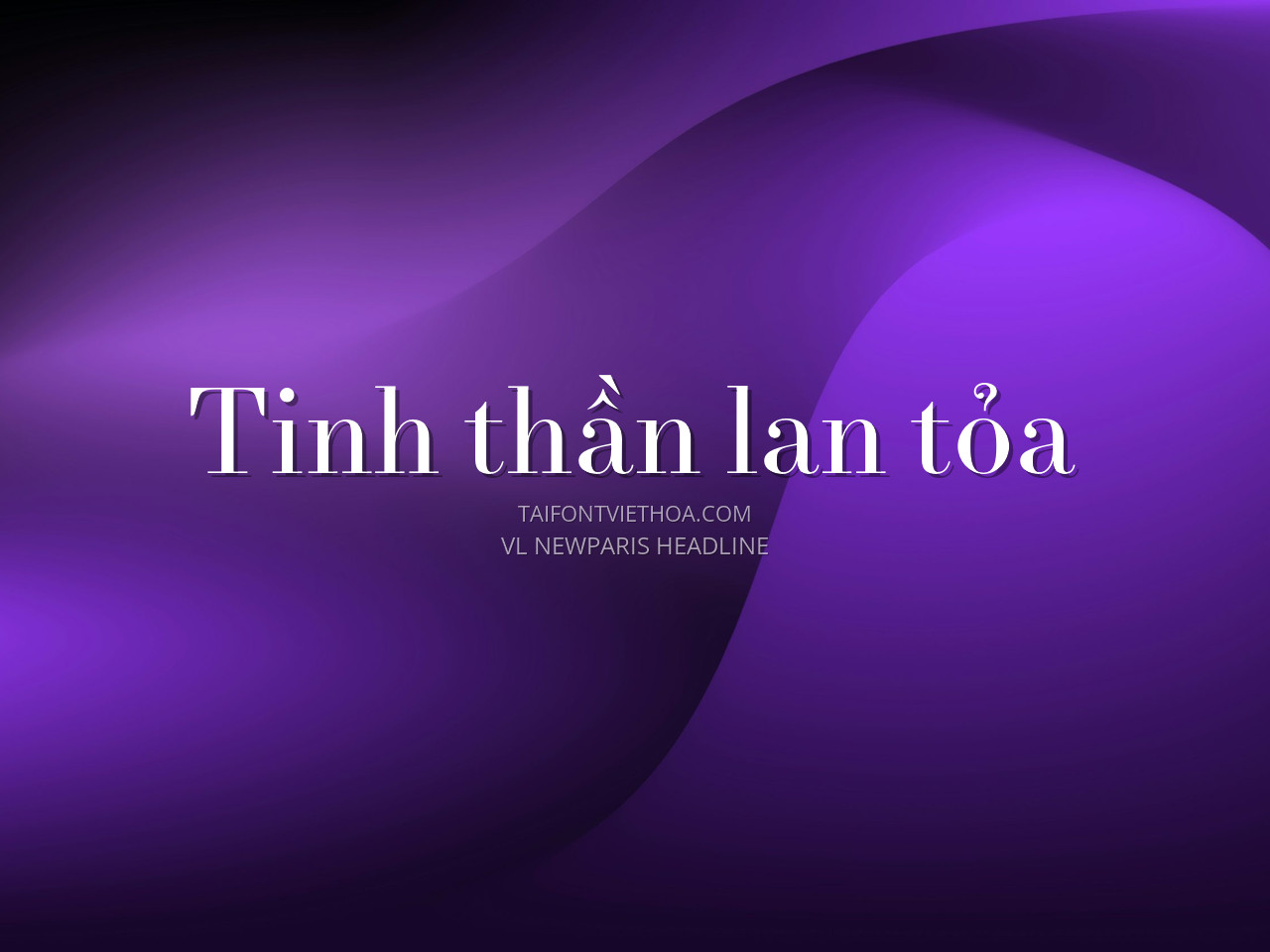
Font việt hóa VL Newparis Headline
Giới thiệu về font VL Newparis Headline
VL Newparis Headline là một kiểu chữ serif hiện đại cao cấp được thiết kế đặc biệt dành cho các tiêu đề lớn, tạo ấn tượng mạnh mẽ ngay từ ánh nhìn đầu tiên. Font mang đậm phong cách biên tập chuyên nghiệp, thường thấy trong các tạp chí thời trang, catalogue hoặc bộ nhận diện thương hiệu cao cấp. Phiên bản Việt hóa được thực hiện bởi Font Việt Linh, hỗ trợ đầy đủ tiếng Việt với các dấu được xử lý tinh tế, sắc nét. Ngoài tiếng Việt, font còn hỗ trợ hơn 60 ngôn ngữ quốc tế khác nhờ vào hệ mã Latin mở rộng. VL Newparis Headline đã được taifontviethoa.com sưu tầm, chọn lọc và ứng dụng thành công trong nhiều dự án truyền thông, biên tập và thiết kế thương hiệu tại Việt Nam.
Đặc điểm thiết kế và ứng dụng của VL Newparis Headline
Font sở hữu các nét chữ serif có độ thanh thoát cao, độ tương phản rõ ràng giữa nét dày và mảnh, tạo cảm giác tinh tế nhưng không mất đi sự mạnh mẽ. Các đường cong và góc chữ được tối ưu hóa để tạo ra tính thẩm mỹ cao khi sử dụng ở kích thước lớn, đặc biệt là trong các thiết kế tiêu đề, banner hoặc bìa ấn phẩm.
VL Newparis Headline phù hợp cho các thiết kế bìa sách, tiêu đề tạp chí, branding sản phẩm cao cấp, poster thời trang, thiết kế bao bì, bộ nhận diện thương hiệu và quảng bá truyền thông. Ngành nghề lý tưởng: thời trang, mỹ phẩm, xuất bản, bất động sản cao cấp, truyền thông sáng tạo và thiết kế nội thất.